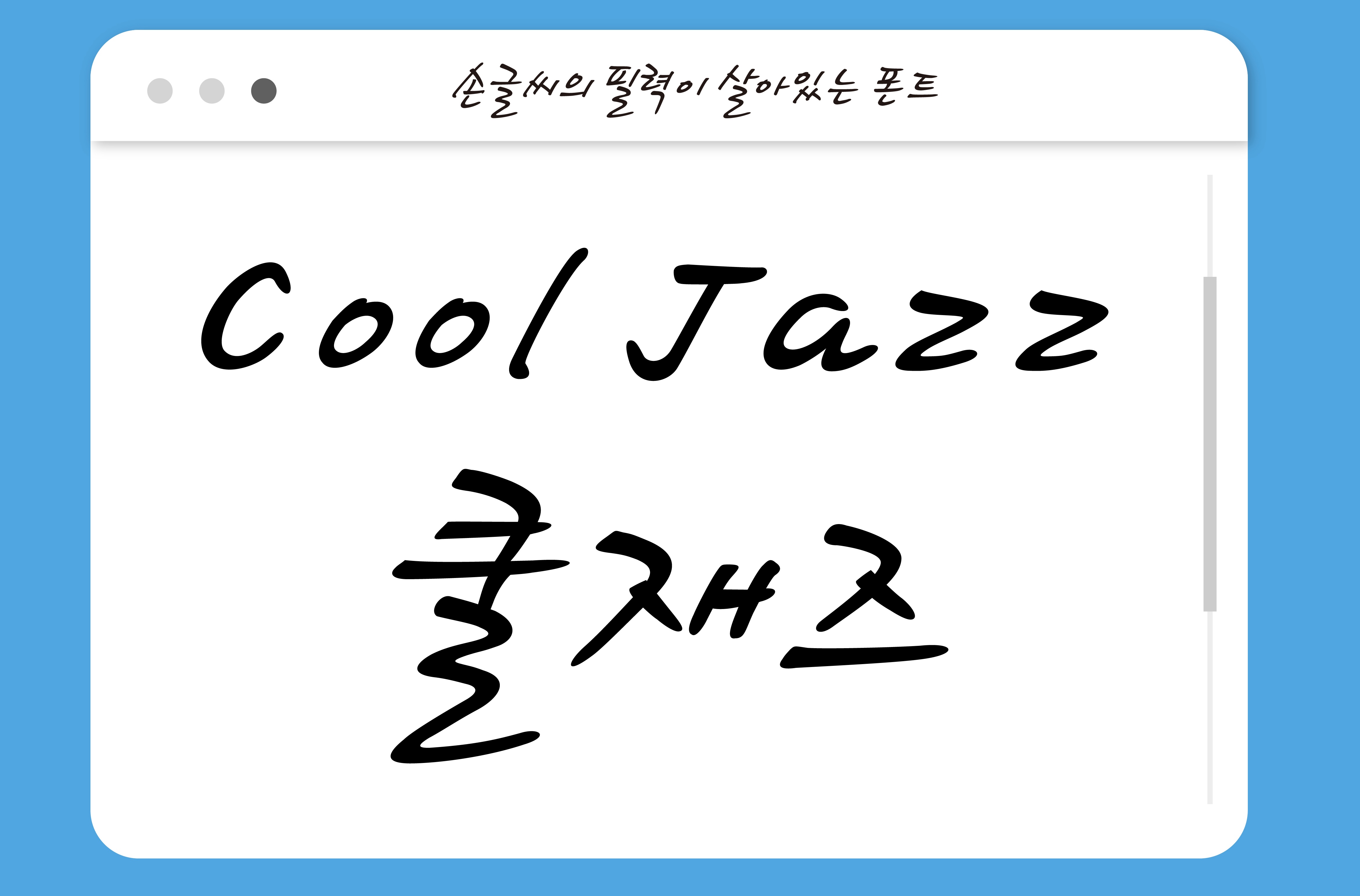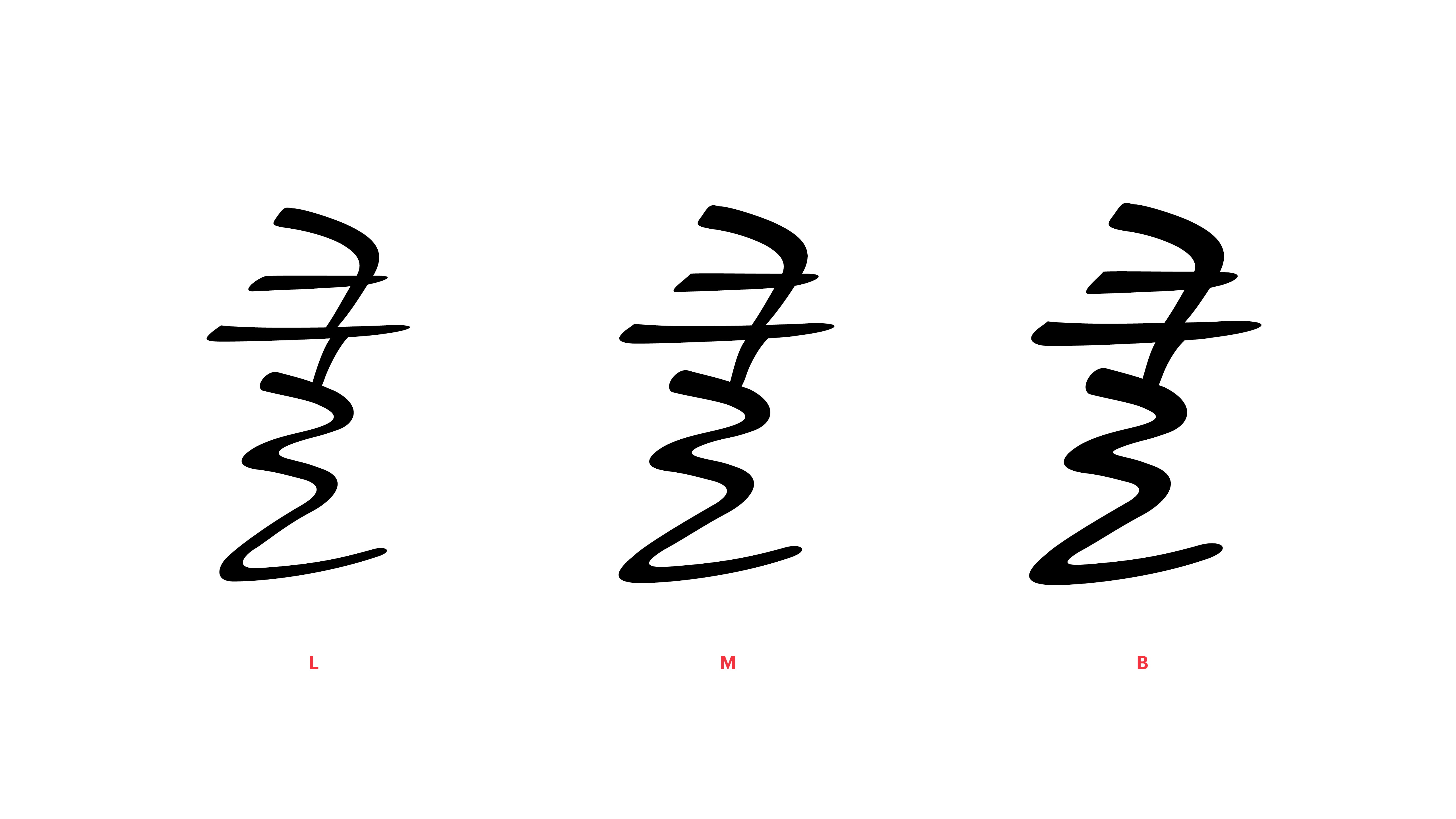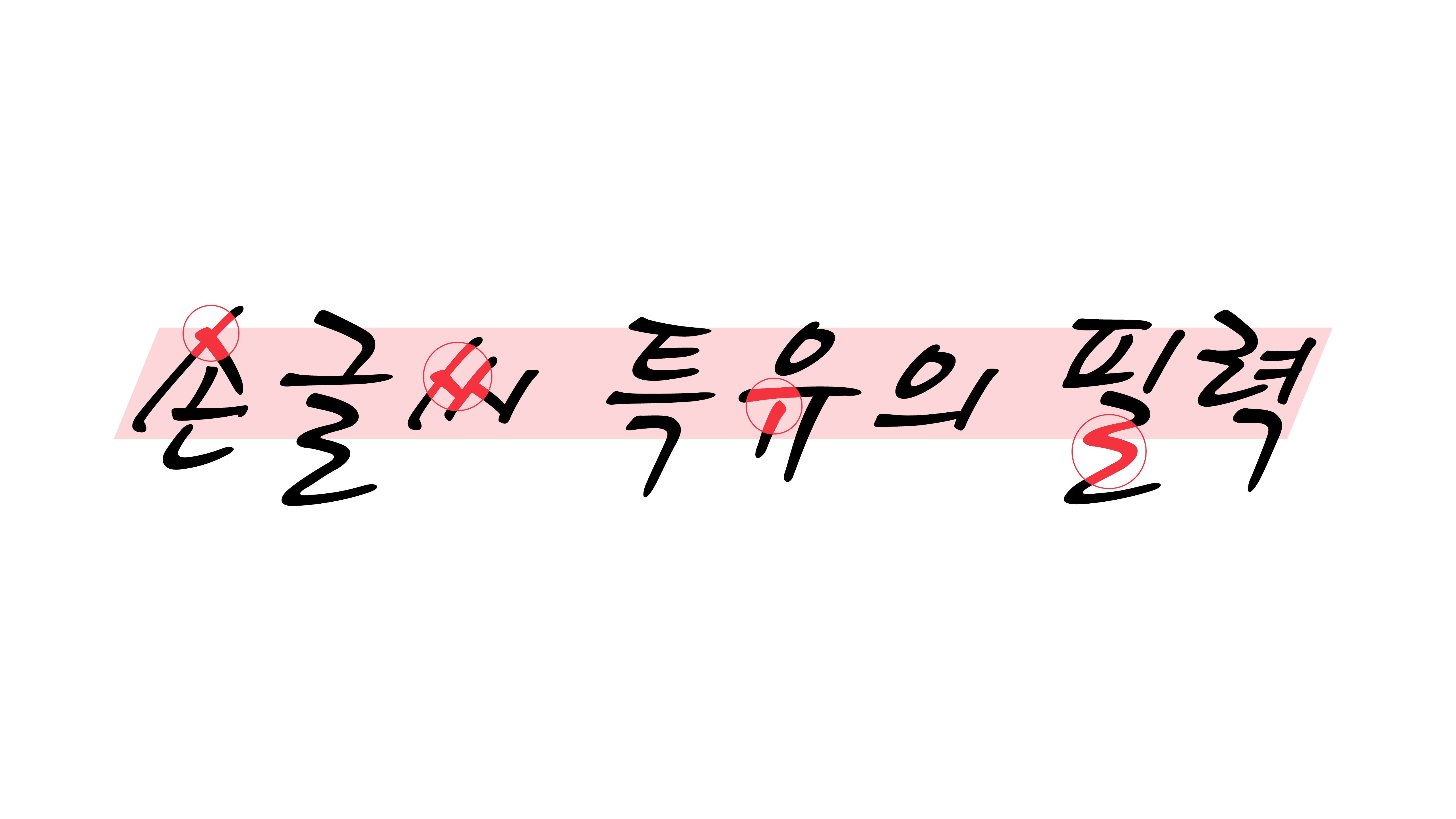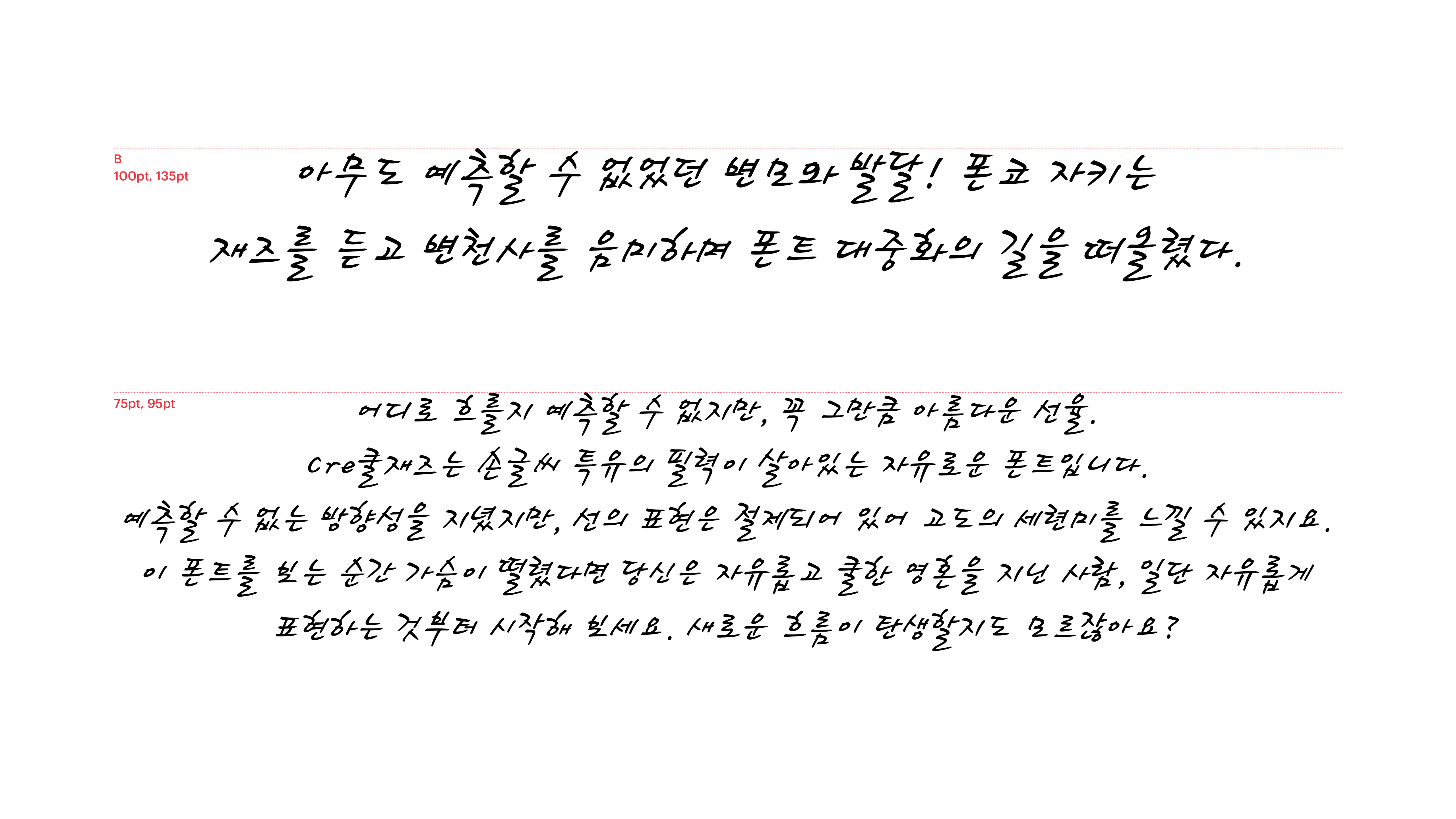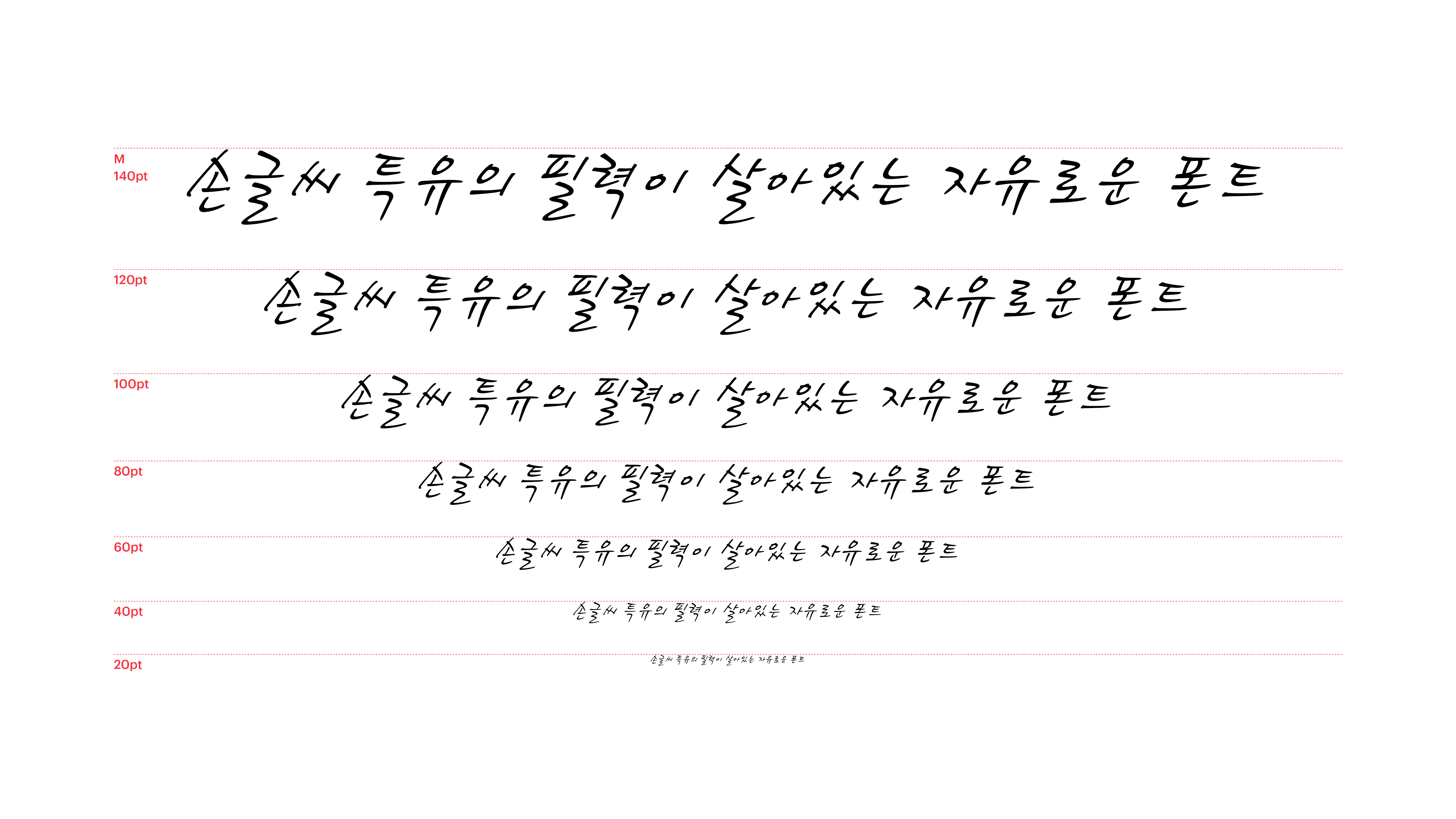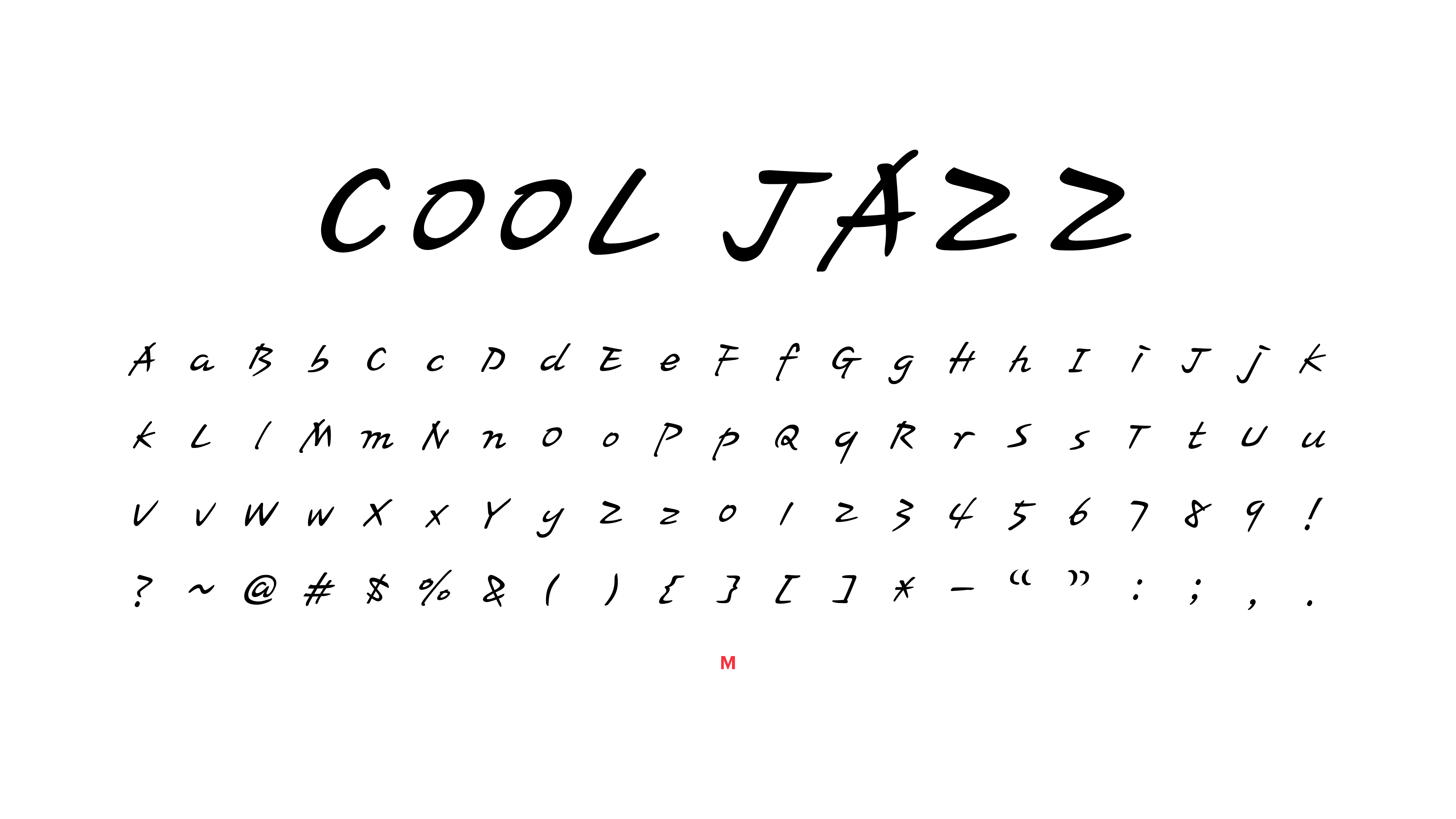
어디로 흐를지 예측할 수 없지만, 꼭 그만큼 아름다운 선율. Cre쿨재즈는 손글씨 특유의 필력이 살아있는 자유로운 폰트입니다. 예측할 수 없는 방향성을 지녔지만, 선의 표현은 절제되어 있어 고도의 세련미를 느낄 수 있지요. 이 폰트를 보는 순간 가슴이 떨렸다면 당신은 자유롭고 쿨한 영혼을 지닌 사람, 일단 자유롭게 표현하는 것부터 시작해보세요. 새로운 흐름이 탄생할지도 모르잖아요?
Yoon Cre쿨재즈